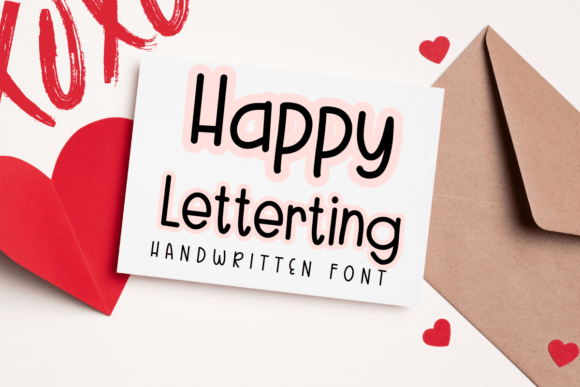
Happy Lettering
適切なデザイン要素を見つけるのは難しい場合がありますが、Happy Letteringは作品を即座に引き立てる優れたコレクションを提供します。
POD(オンデマンド印刷)製品、結婚式の招待状、またはソーシャルメディアのグラフィックを作成している場合でも、Happy Letteringは理想的です。